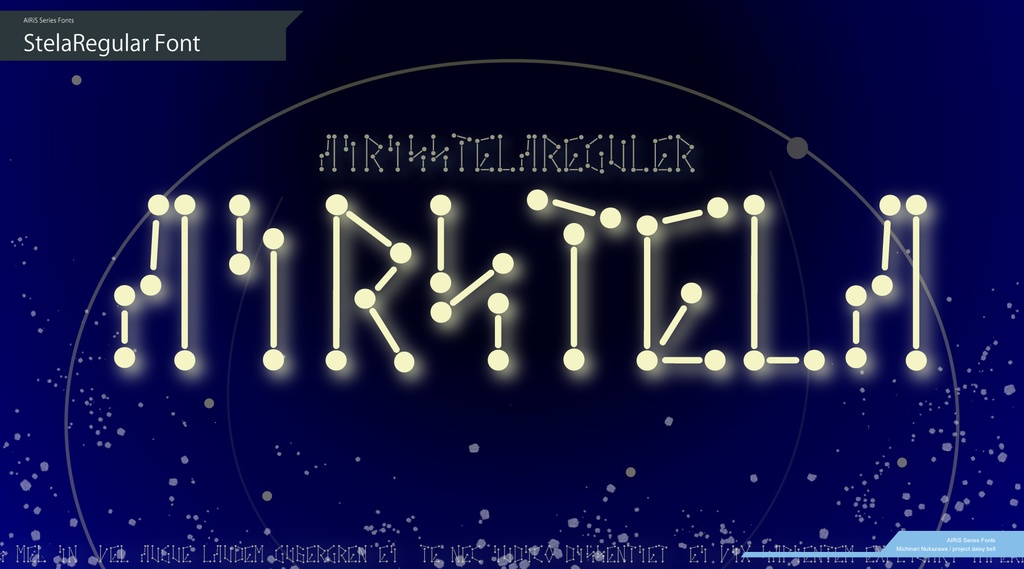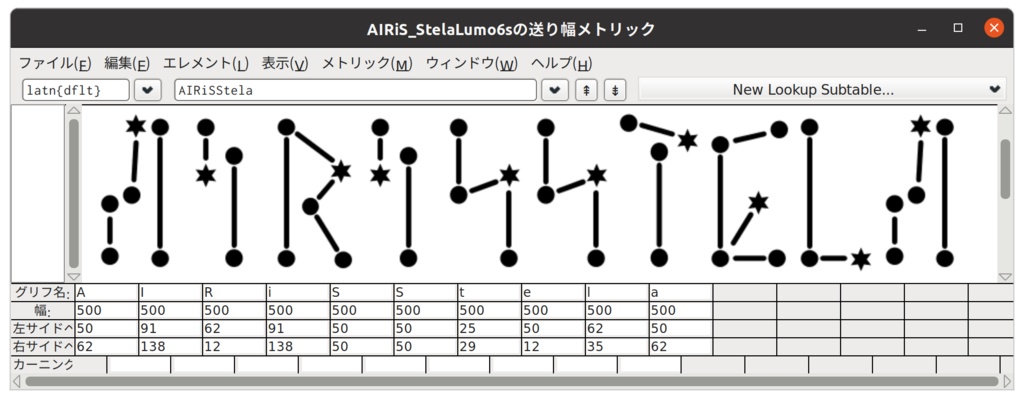
星空・星座風フリーフォント集 Stela* シリーズ
星空/星座風ラテン・アルファベットのフォントセットです。 ラテン・アルファベットと数字(A-Z)(一部a-z,0-9)を収録。 宇宙・ロケット・星空・天体観測・星座占いなどのデザイン表紙、サブタイトルなどに。 商用可。 ライセンスはRuneAMNシリーズフォントに準じます。 https://github.com/MichinariNukazawa/RuneAssignMN_Series_Fonts/ 収録書体: AIRiS_StelaRegular AIRiS_StelaBold(太字) AIRiS_StelaNarrow(長体) AIRiS_StelaLumo4(フレア付きスター書体) AIRiS_StelaLumo6s(フレア付きスター書体) 更新履歴: -2020/11/07アップデートしました(新フォント追加) -2020/11/10アップデートしました(各書体に数字を追加[0-9]) -2020/12/29アップデートしました(小文字・漢字を追加) -2021/07/30アップデートしました(新フォント追加) 追加書体・追加文字を収録したPro版をBOOTH他にて販売中: https://daisy-bell.booth.pm/items/2414170